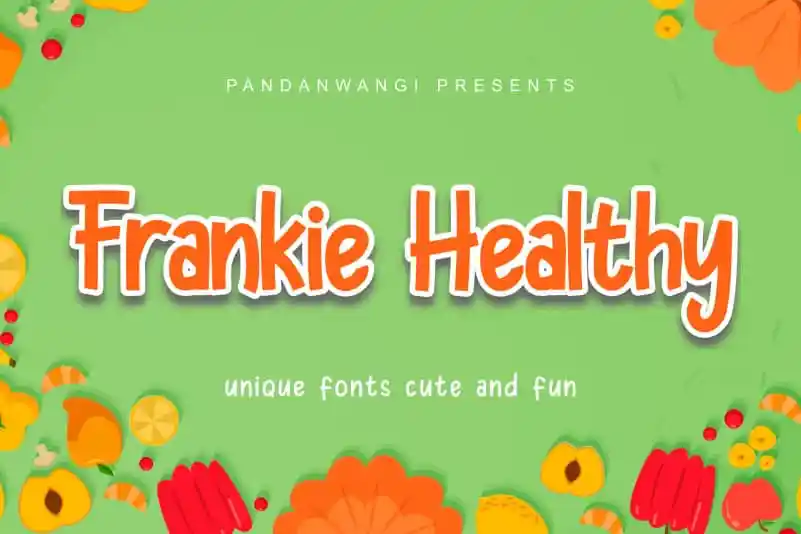
A Frankie Healthy Font é uma fonte de exibição encantadora e colorida projetada para inspirar a criatividade. Essa fonte tem uma sensação autêntica que pode ser usada de forma lúdica e divertida, desde a criação de convites de casamento até a arte de papelaria e cartões de cumprimentos. Ela também é ótima para utilizar em posts visíveis nas redes sociais. O único limite é sua imaginação! A Frankie Healthy Font é perfeita para quem deseja dar um toque divertido e colorido a qualquer projeto, seja ele um convite de casamento delicado ou uma lembrança personalizada. Se você gosta de criar designs que são ao mesmo tempo criativos e alegres, essa fonte pode ser sua escolha perfeita para agregar brilho à sua arte digital.